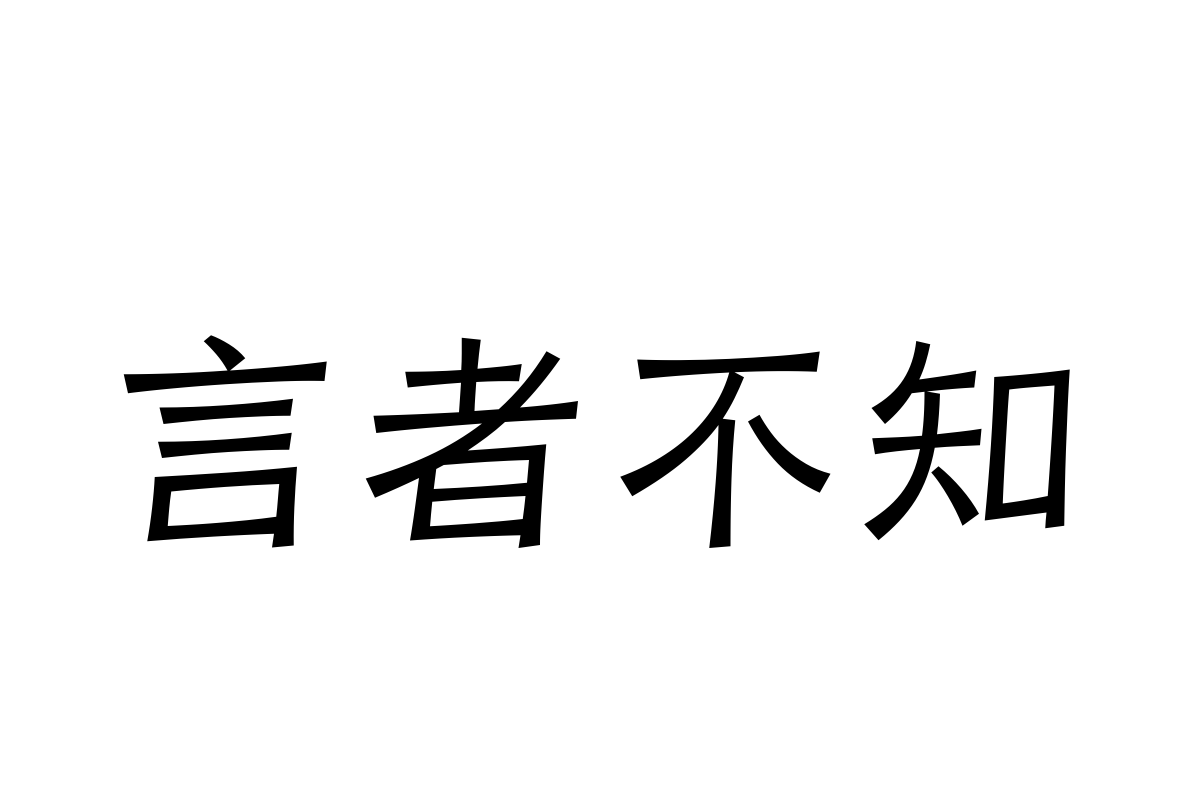
汉仪瑞云袖舞 45W是一款具有独特艺术风格的字体,它采用了传统的书法元素和现代的设计手法相结合的方式,创造出了一种既古典又现代的视觉效果。这款字体的笔画流畅自然,结构严谨,线条粗细适中,既有力度又有柔美,给人一种优雅而富有韵味的感觉。
在设计上,汉仪瑞云袖舞 45W注重细节的处理,无论是笔画的起笔、转折还是收笔,都经过精心雕琢,使得整体看起来更加和谐统一。同时,这款字体还特别注重字间距和行距的调整,使得文字排列得更加整齐有序,提高了阅读的舒适度。
总的来说,汉仪瑞云袖舞 45W是一款非常优秀的字体,它不仅能够用于各种印刷品的设计,还能够为网站、广告等视觉设计作品增添一份独特的艺术气息。无论是作为标题、正文还是装饰元素,都能够展现出其独特的魅力。